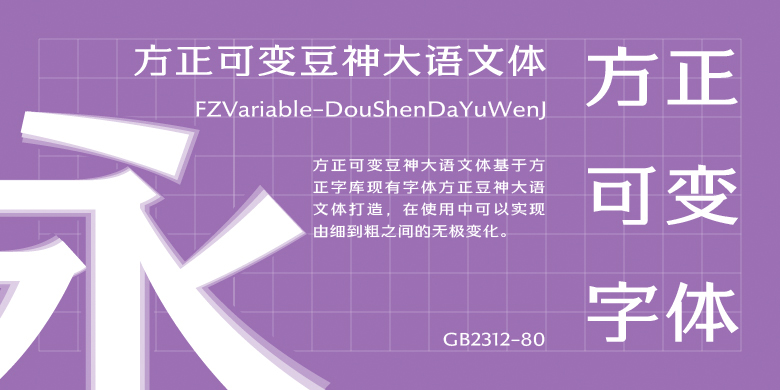
正可变豆神大语文体字体支持文字粗细无级调节,设计师通过调整字重轴(Weight)的变化,可以实现字形的平滑连续的细微调整,满足不同版式的设计需求。 方正豆神大语文体是为豆神教育科技(北京)股份有限公司旗下品牌“豆神大语文”而设计的定制字体。本字体以豆神大语文logo为字体创作基础,经过取舍优化延展设计成全套字库。其字形扁方、重心平稳,体现教育企业给人的亲和与信任感。中文笔形略带宋意,笔画间渗透着中华传统文化的传承,正与中华传统学科——语文的特性相契合。横画尾部向上翘起,象征企业长远发展,同时也表达对万千学子蒸蒸日上的美好祝愿。豆神大语文体共有4个字重,可以适应标题、文本等不同的使用需求。西文与中文匹配设计,字形偏扁,采用半衬线形式,笔画末端弧度与中文相呼应。力求在保持拉丁文书写逻辑的基础上,视觉上与中文相统一。